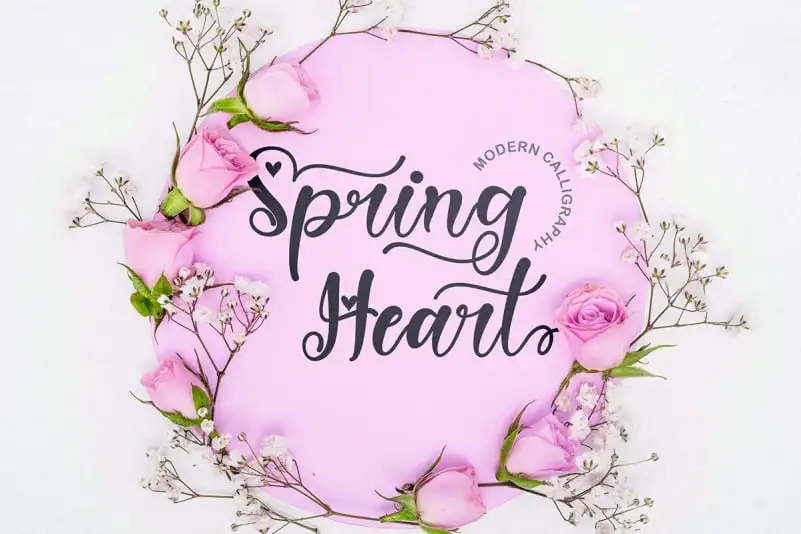
Spring Heart Calligraphy Font – Download Grátis
Esta fonte é chamada “Spring Heart Calligraphy Font”, combinando a primavera e um coração acolhedor. Esta fonte é bela, única e muito fácil de usar. Ela inclui detalhes encantadores nos caracteres, que são fáceis de aplicar, além das instruções para usá-los de maneira eficiente. A fonte se destina perfeitamente a projetos relacionados à primavera, casamentos, Dia da Mãe, Dia do Pai, dia de São Patricio e Dia da Terra, entre outros. Ela é uma escolha ideal para aqueles que desejam um toque especial em seus trabalhos gráficos. Com o “Spring Heart Calligraphy Font”, você pode criar mensagens acolhedoras e alegres, perfeitas para ambientes primaveris e festivais.